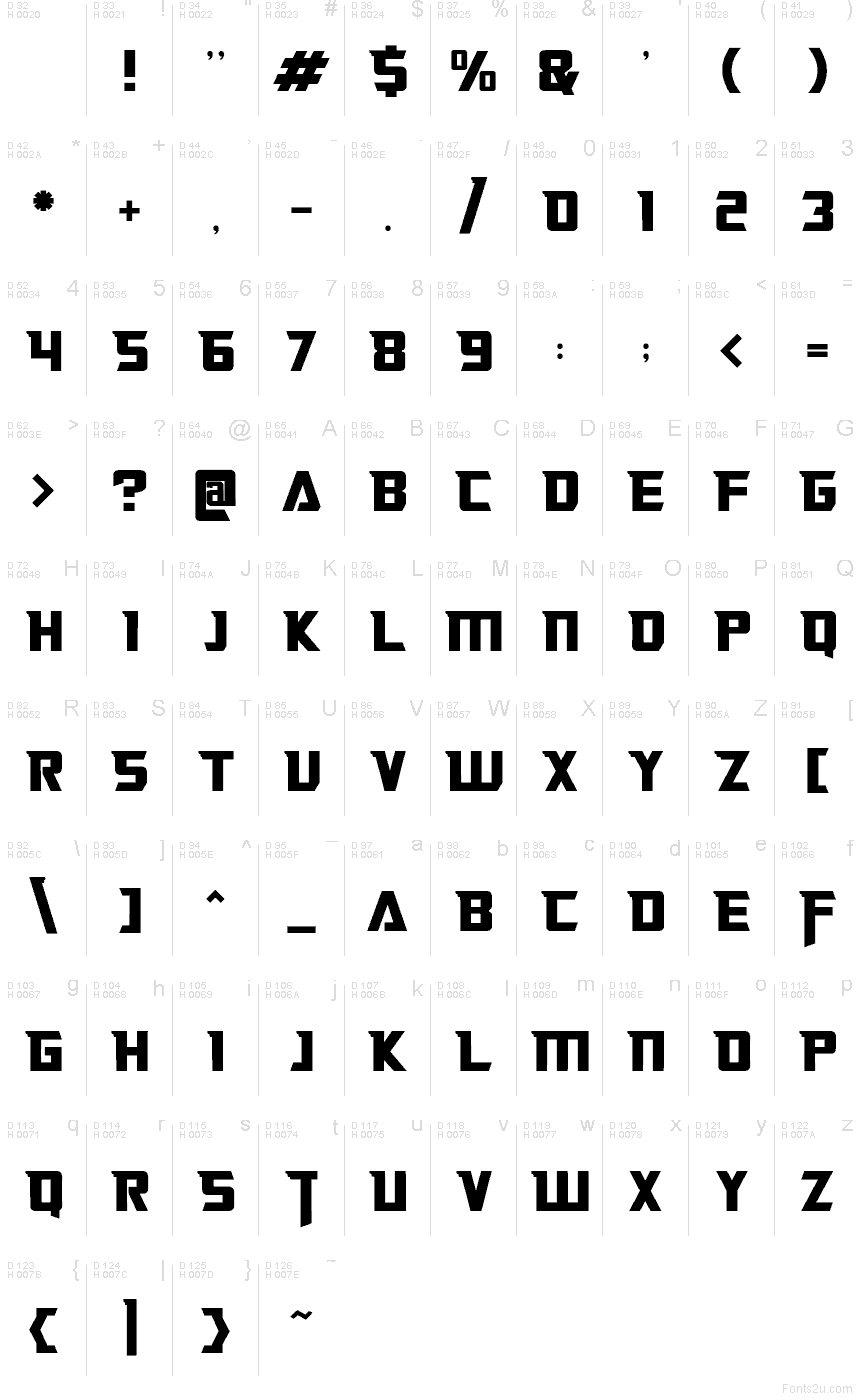
Turbo Type od Putracetol Studio je bezplatné techno display písmo. Vyznačuje se vysokými, blokovými tvary a ostrými, šikmo řezanými rohy, které písmu dodávají strojový vzhled inspirovaný videohrami. Opakující se výřezy udržují design pevný a kompaktní, díky čemuž působí font spíše jako technický návrh než jen jako geometrická abstrakce.
Nejlépe vynikne v esportovém brandingu, arkádových plakátech, grafice pro streamery, sci-fi titulcích nebo úvodních obrazovkách aplikací, kde jeho zařezané hrany fungují lépe než běžné bezpatkové písmo. U krátkých nadpisů, log či obalů pro herní vybavení dodává jeho čtvercový rytmus a hutná vertikální přítomnost výraznější charakter.